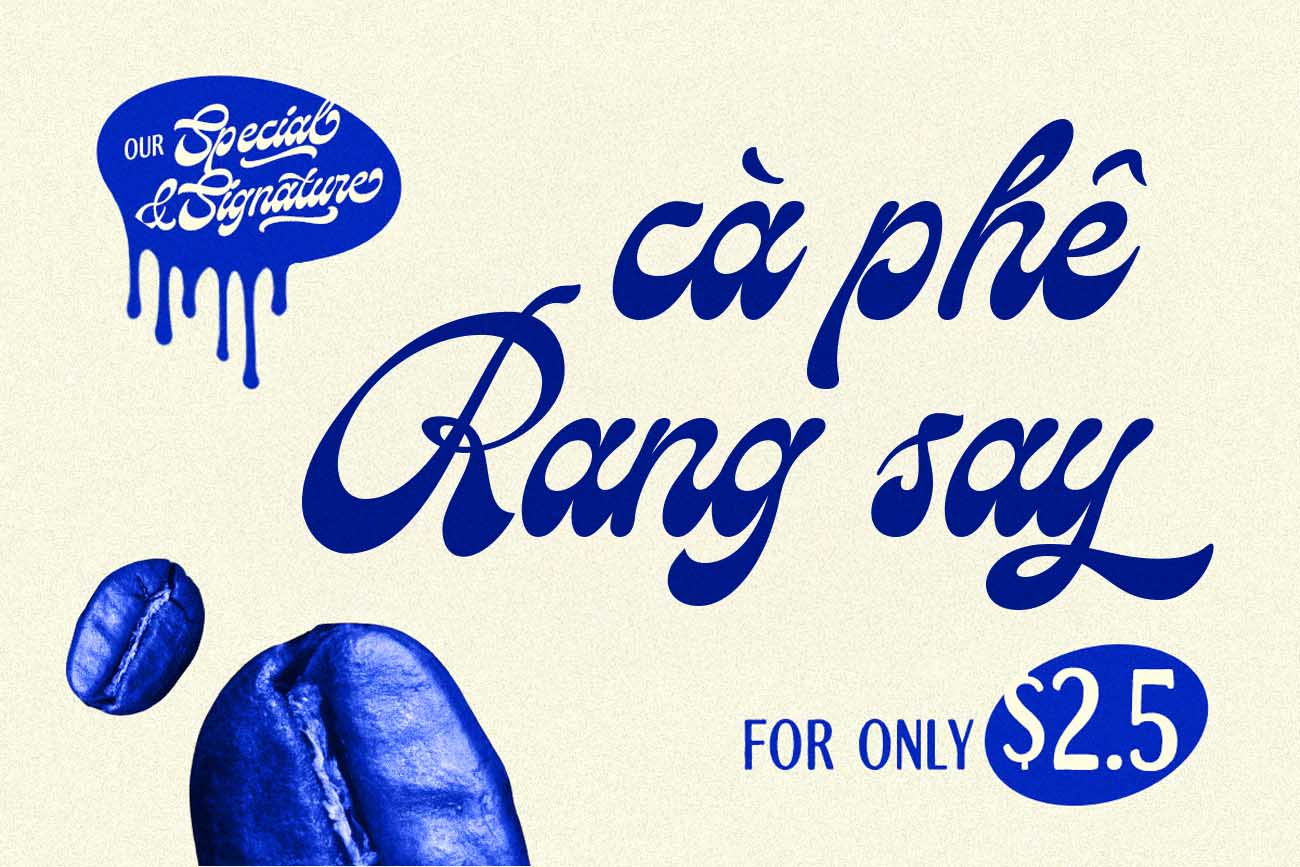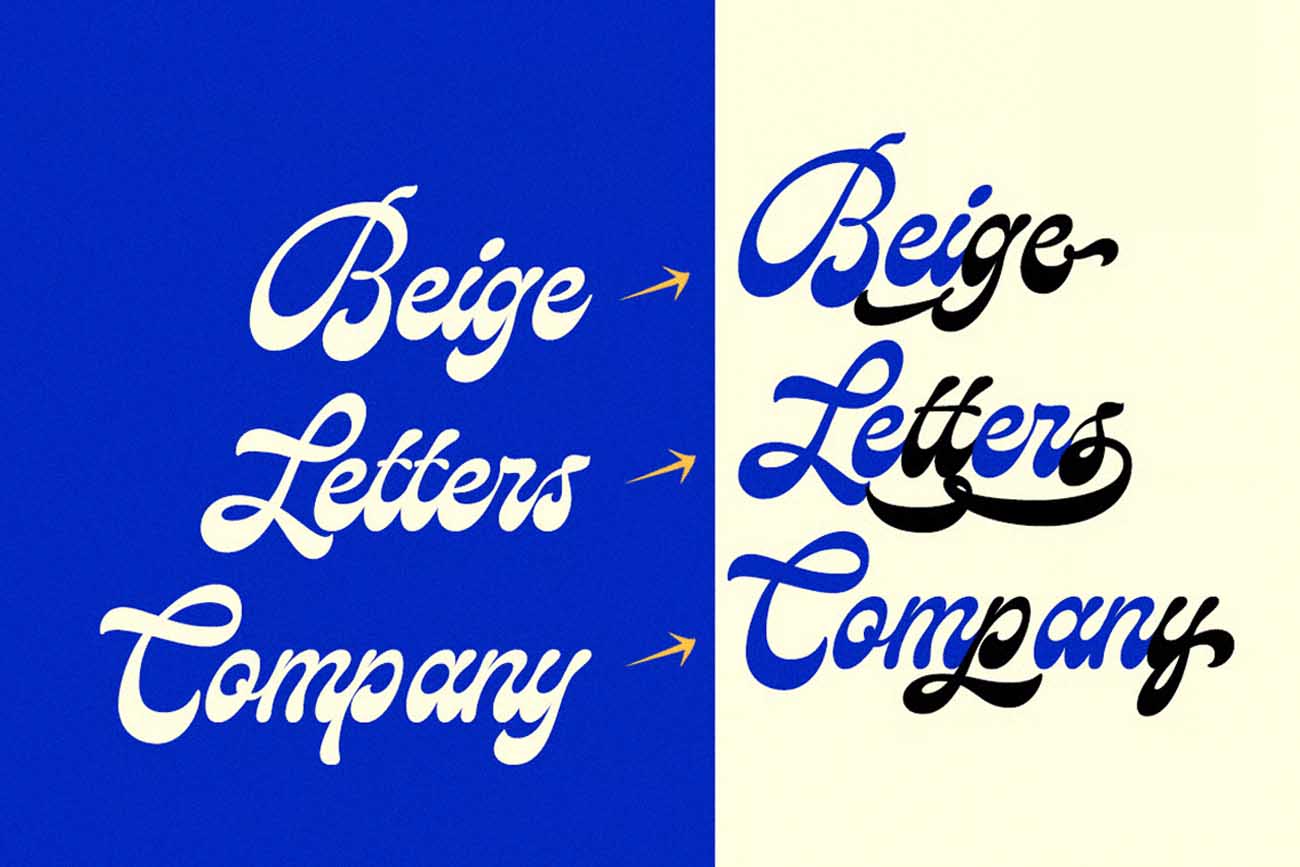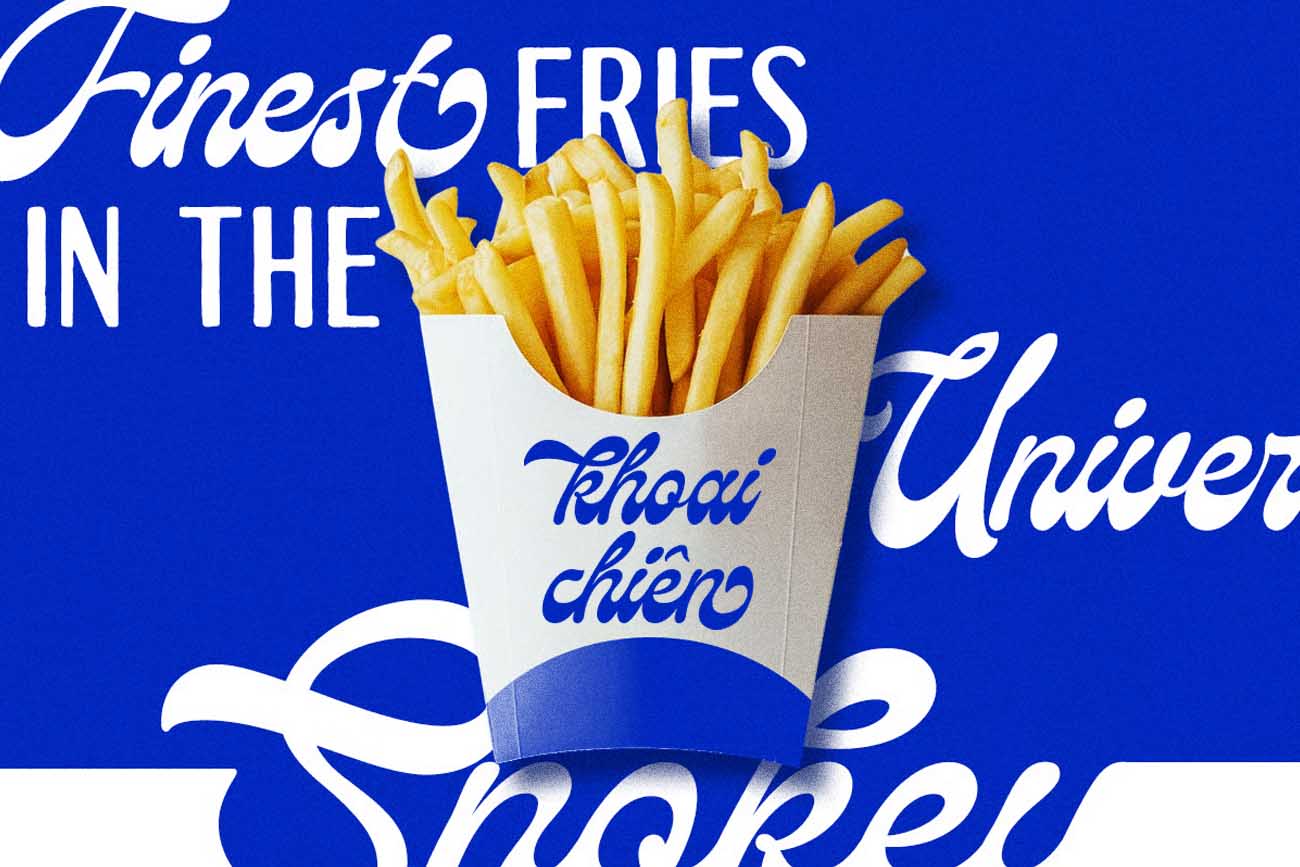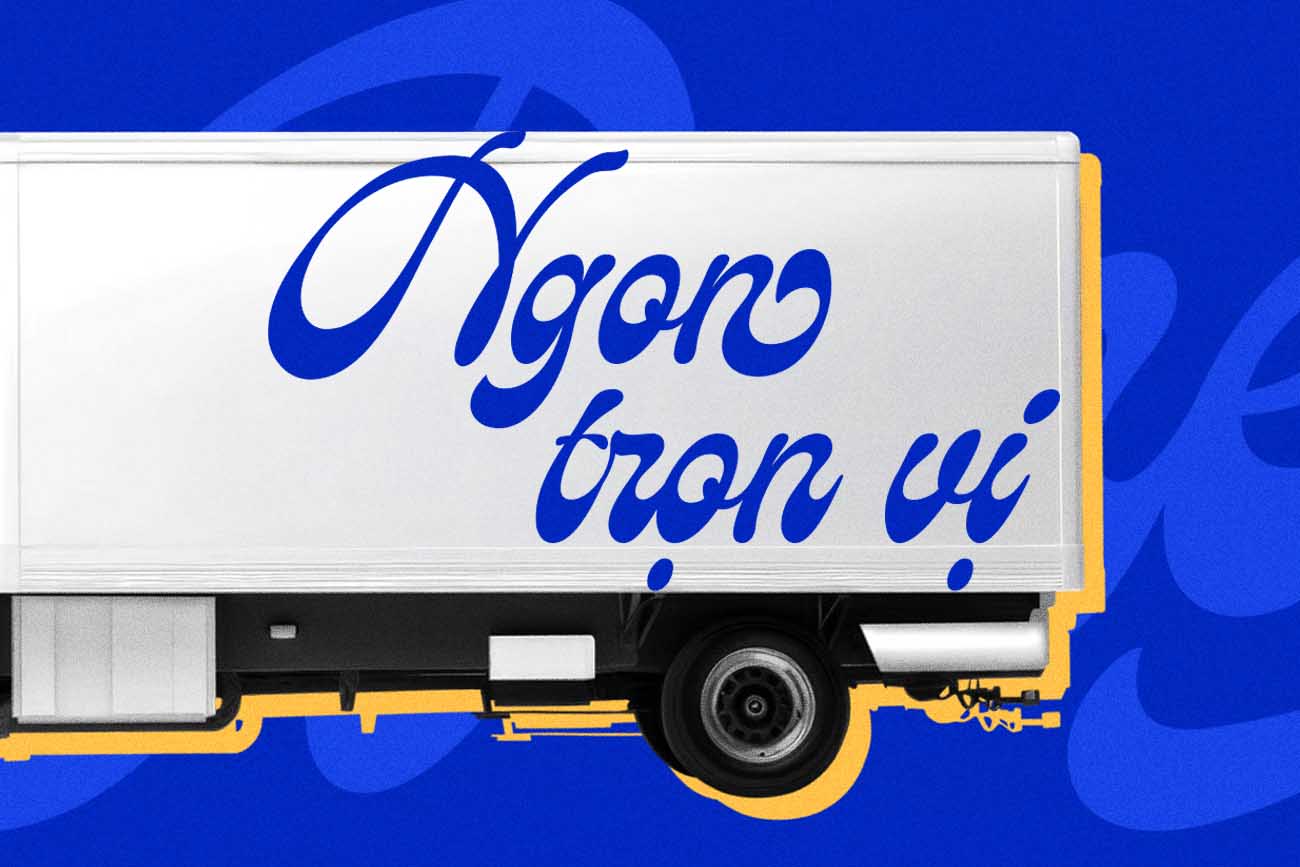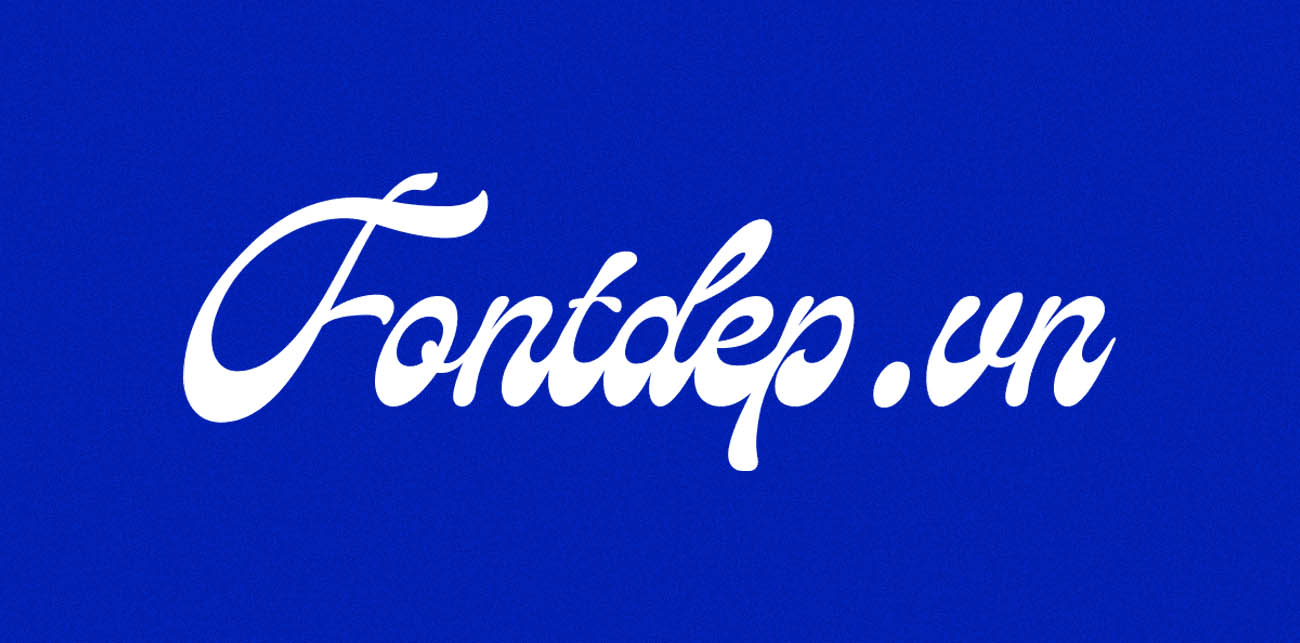
Phông chữ viết tay phong cách retro cổ điển - TH Relgone Việt hóa
Tác giả Letterhend
Giới thiệu font chữ Relgone
Font chữ Relgone là một trong những lựa chọn nổi bật dành cho designer yêu thích sự mềm mại và nghệ thuật. Được thiết kế theo phong cách script handwritten (chữ viết tay), Relgone mang trong mình hơi thở retro cổ điển kết hợp sự tự nhiên, uyển chuyển của nét bút tay.
Điểm đặc biệt của font nằm ở những alternate characters – ký tự thay thế độc đáo, giúp người dùng dễ dàng tạo nên những thiết kế mang tính cá nhân hóa cao. Mỗi đường cong, mỗi nét nối đều tạo cảm giác gần gũi, chân thực nhưng không kém phần sang trọng.
Font Relgone Việt hóa bởi Phạm Sơn
Phiên bản Relgone Việt hóa được thực hiện bởi Phạm Sơn, đảm bảo hỗ trợ đầy đủ dấu tiếng Việt, kerning hợp lý và không lỗi hiển thị. Nhờ đó, designer tại Việt Nam có thể thoải mái ứng dụng font trong nhiều dự án, từ thiết kế logo, bao bì sản phẩm, poster cho đến typography nghệ thuật.
Sự tinh chỉnh tỉ mỉ trong quá trình Việt hóa giúp Relgone không chỉ giữ nguyên tinh thần retro quốc tế mà còn trở nên gần gũi, dễ sử dụng với ngôn ngữ tiếng Việt.
Ứng dụng thực tiễn
Font chữ Relgone đặc biệt phù hợp với:
• Thiết kế logo: Tạo dấu ấn thương hiệu mang phong cách cá nhân, nghệ thuật.
• Poster & banner: Thu hút ánh nhìn nhờ nét chữ mềm mại, hoài cổ.
• Bao bì sản phẩm: Nhấn mạnh sự thủ công, tinh tế.
• Typography nghệ thuật: Mang lại cảm xúc hoài niệm và sang trọng.
Relgone dễ dàng kết hợp cùng các font sans-serif hiện đại, tạo nên sự đối lập thú vị trong bố cục thiết kế.
Nếu bạn đang tìm kiếm một font chữ script retro vừa tinh tế, vừa hỗ trợ đầy đủ tiếng Việt, thì Relgone Việt hóa bởi Phạm Sơn là lựa chọn hoàn hảo. Với nét chữ mềm mại, ký tự thay thế phong phú và sự chỉnh chu trong Việt hóa, Relgone chắc chắn sẽ giúp tác phẩm của bạn trở nên độc đáo và chuyên nghiệp hơn.